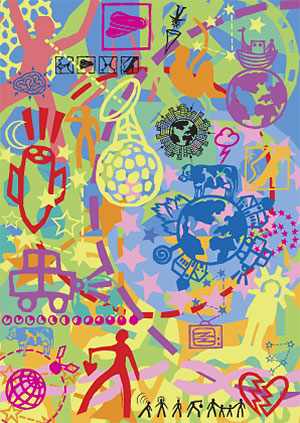
Sammelkarte: ElementaryEine Fontcard aus dem Januar 1995, entworfen von Nicole Kapitza.
Die farbenfrohe Karte warb für ihren Piktogramm-Font FF Elementary,
der aus drei Gruppen holzschnittartiger Symbole besteht: Earth, Life und Space.
![]() Nicole Kapitza lebte 1995 in Stuttgart und hatte gerade ihr
Grafik-Design-Studium abgeschlossen. Ihr Pikto-Font FF Elementary entstand mit Unterstützung
von Frank Heine (1964 – 2003), der bei FontFont zu diesem Zeitpunkt
bereits die Schriften FF Chelsea und FF Instanter herausgebracht hat und bei
Emigre den Bestseller Remedy.
Zeichen, Symbole und Piktogramme faszinierten Nicole Kapitza schon vor ihrem Studium. »Eigentlich gibt es Bildmarken für fast jeden Lebensbereich. Doch FF Elementary visualisiert einige Themen, die in herkömmlichen Pikto-Fonts bisher nicht angesprochen wurden: Umwelt, Ängste, zwischenmenschliche Beziehungen, Sex, Gewalt, Zukunft, Natur, das Universum – Themen, die im Leben vieler Menschen eine wichtige Rolle spielen.« schrieb sie damals in einem Read-me-Text zur Schriftfamilie FF Elementary. Eine technische Besonderheit von FF Elementary liegt in der Kombinationsmöglichkeit mancher Zeichen durch einfaches Übereinandertippen (Zeichen mit Null-Weite), zum Beispiel eine feststehende Weltkugel, auf deren Oberfläche sich verschiedene Häuser und Lebewesen ansiedeln können. Auf diese Art lassen sich Hunderte immer wieder anders aussehende Illustrationen herstellen. 2004 gründete Nicole Kapitza mit ihrer Schwester Petra in London ein eigenes Designbüro. Ihr Schwerpunkt liegt in der Gestaltung von Ausstellungen, Büchern, Postern und neuen Medien.